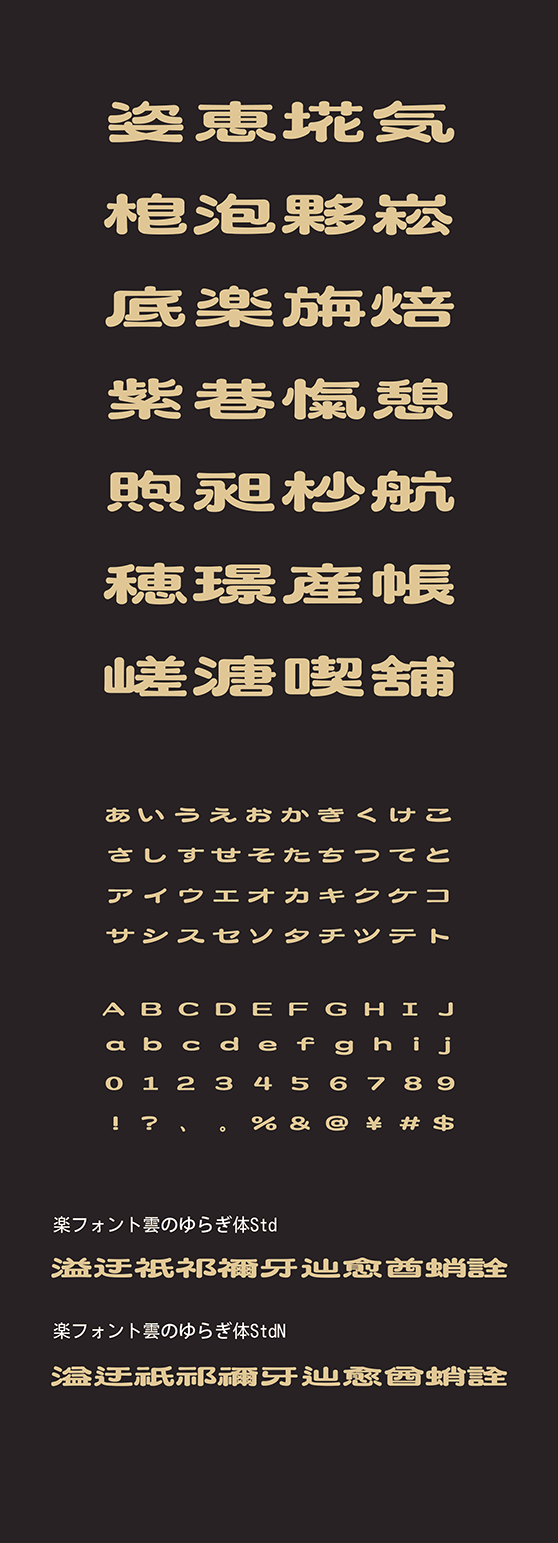
楽フォント
雲のゆらぎ体 (くものゆらぎたい Std・StdN同梱)
KumonoyuragitaiStd, KumonoyuragitaiStdN
丸みのあるやさしい線と広めの字形設計により、柔らかく読みやすい表情を持つフォントです。漢字と仮名の丸みとバランスを統一し、親しみやすく現代的な雰囲気を実現しました。UI や教育、生活系ブランドなど、やさしさと安心感を伝えたいデザインに最適です。